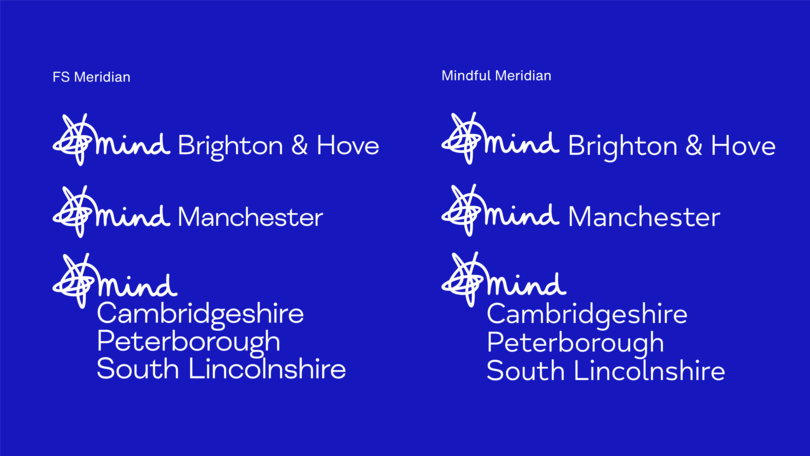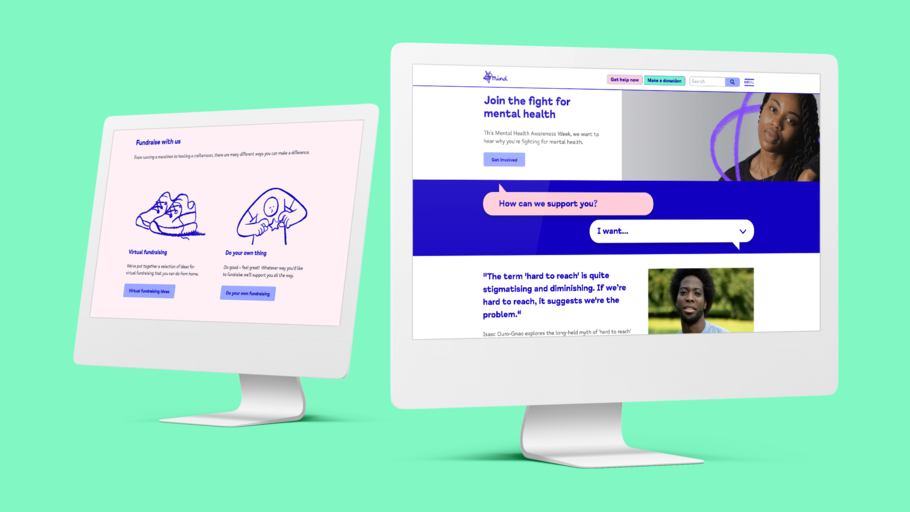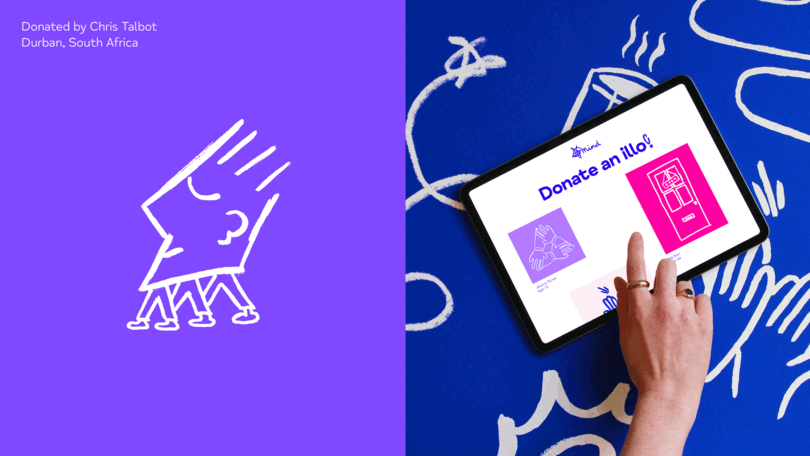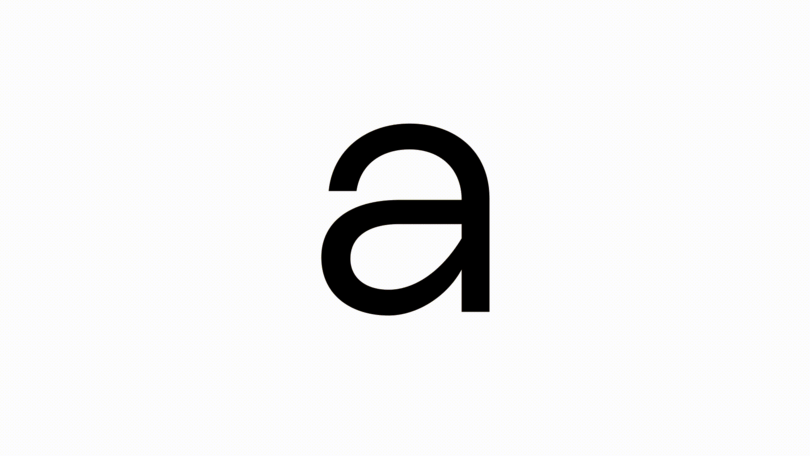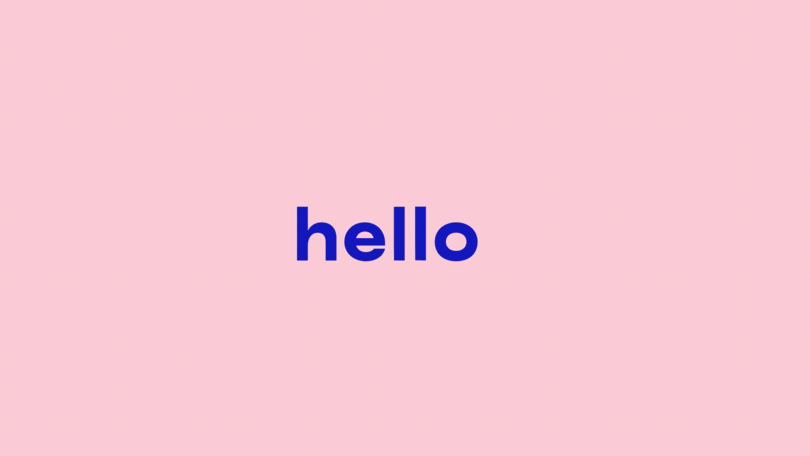
Une nouvelle police au service de la clarté numérique de Mind.
“ « L’accessibilité en typographie ne repose pas uniquement sur le design ou la forme d’une lettre. Il s’agit aussi en grande partie d’application, de couleur, de contraste et de typographie à proprement parler. » ”
Phil Garnham, Creative Type Director.
Après des années de campagne visant à sensibiliser et à apporter une meilleure compréhension de la santé mentale, le temps était venu pour Mind, une association caritative, de renouveler son identité visuelle emblématique. En Angleterre et au Pays de Galles, son logo gribouillé est largement reconnu. Mais les réseaux sociaux et les autres espaces numériques ont créé de nouvelles exigences pour l’association. En partenariat avec l’agence DesignStudio, le Studio Monotype a développé Mind Meridian – une police améliorée qui place la chaleur et l’accessibilité au cœur de la marque.
Le brief.
« Mind voulait un partenaire pour améliorer sa marque, son histoire et sa production visuelle afin de les communiquer au reste du monde », explique Vinay Mistry, directeur de la création chez DesignStudio, ayant travaillé sur cette mise à jour. « Avec de nombreuses recherches sur le travail caritatif et un aperçu des expériences vécues par les employés ou bénévoles, nous avons commencé à comprendre les points de tension où certains éléments n’étaient pas aussi efficaces que le reste. »
Mind, la plus grande association britannique dans le domaine de la santé mentale, utilisait plusieurs polices acquises au fil des ans et avec des styles variés, à présent confrontées à de nouvelles exigences en termes d’accessibilité. Rendre la marque plus accessible au public diversifié de l’association était une partie importante du brief pour la nouvelle police et le système de conception. Cela devait également être facile à utiliser pour les bénévoles et les associations locales de Mind, qu’ils aient une expérience ou non dans le design.
Comme pour beaucoup d’autres marques, la plupart des interactions de Mind se passent désormais en ligne, rendant le domaine numérique absolument essentiel pour atteindre son audience. Un des principaux objectifs était donc de renouveler la palette typographique de Mind pour lui permettre à la fois de communiquer avec clarté à travers ces plateformes et de s’exprimer sans effort à travers sa typographie. Il fallait également s’appuyer sur le capital de marque que représente le logo gribouillé de Mind, qui a toujours été un élément très apprécié de la marque.
“ « En créant une police qui fonctionne très bien partout, nous voulions nous assurer qu’il s’agirait de la chose la plus simple à utiliser, que ce soit en ligne ou sur papier, en très grand pour les affiches et signalétiques ou en tout petit pour apporter l’information à ceux qui en ont vraiment besoin. » ”
Vinay Mistry, Creative Director, DesignStudio.
Il était essentiel que cette nouvelle police incarne la chaleur et la gravité qui font la réputation de Mind. L’association a été créée pour tendre la main aux gens et entrer en contact avec eux. Sa mission a pris une nouvelle tournure devant les défis de santé mentale que la pandémie a accentués. Ce rebranding devait exprimer la même humanité. Mistry le dit ainsi : « Les gens ont besoin de savoir instantanément qu’ils peuvent se fier à cette association. Cela a été une partie essentielle du brief pour la typographie. »
La solution.
DesignStudio avait déjà développé une nouvelle palette de couleurs qui représenterait « l’esprit combatif » de Mind : suffisamment modulable pour des tons plus doux lorsque nécessaire et plus vibrants quand le ton de voix se doit d’être plus percutant. Un reflet du large éventail de la mission de Mind – qui consiste à apporter du soutien mais aussi à demander des comptes au gouvernement et aux décideurs politiques.
La nouvelle police de caractères de l’association a été conçue pour s’harmoniser avec ce rebranding. Elle conserve la vitalité gribouillée de Mind tout en répondant aux besoins fonctionnels de l’association – en particulier l’accessibilité. Mind Meridian est lisible pour les personnes souffrant de déficiences visuelles et a été ajustée pour s’adapter confortablement aux exécutions locales et manuscrites du logo de l’association.
« L’accessibilité en typographie ne repose pas uniquement sur le design ou la forme d’une lettre », explique Phil Garnham, directeur de la création typographique chez Monotype. « Il s’agit aussi en grande partie d’application, de couleur, de contraste et de typographie à proprement parler. En travaillant ensemble, nous avons établi un ensemble clair de règles autour de cela. »
L’accessibilité en typographie ne repose pas uniquement sur le design ou la forme d’une lettre », explique Phil Garnham, directeur de la création typographique chez Monotype. « Il s’agit aussi en grande partie d’application, de couleur, de contraste et de typographie à proprement parler. En travaillant ensemble, nous avons établi un ensemble clair de règles autour de cela.
FS Meridian a été le point de départ du design. En collaboration avec le DesignStudio, l’équipe du Studio a analysé les formes et l’espacement des lettres, créant des changements subtils comme le rétrécissement des proportions, l’ouverture des espacements, l’augmentation des ascendants et l’accentuation des terminaisons – le tout pour améliorer la respirabilité et le déchiffrage de la police. Ces mises à jour s’appuient sur les recherches approfondies en matière d’accessibilité déjà menées par Monotype pour des marques telles que ING, RNIB et Mencap.
Mind Meridian reflète parfaitement là où Mind se situe aujourd’hui. Elle permet à la marque d’adapter son ton dans le futur et à l’association de continuer son combat pour la santé mentale, sans perdre l’appréciation et la fiabilité du capital de marque acquis dans le passé.